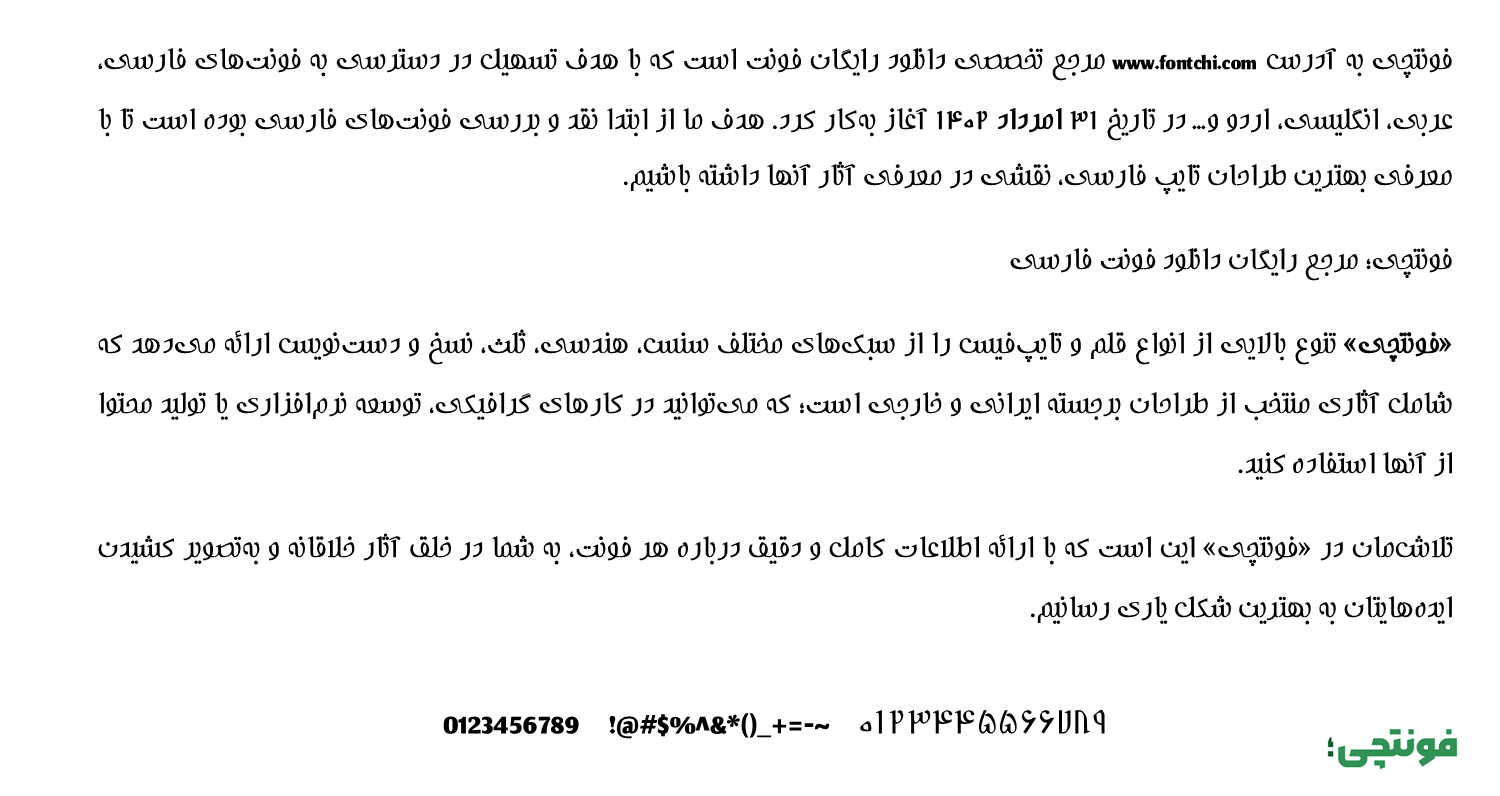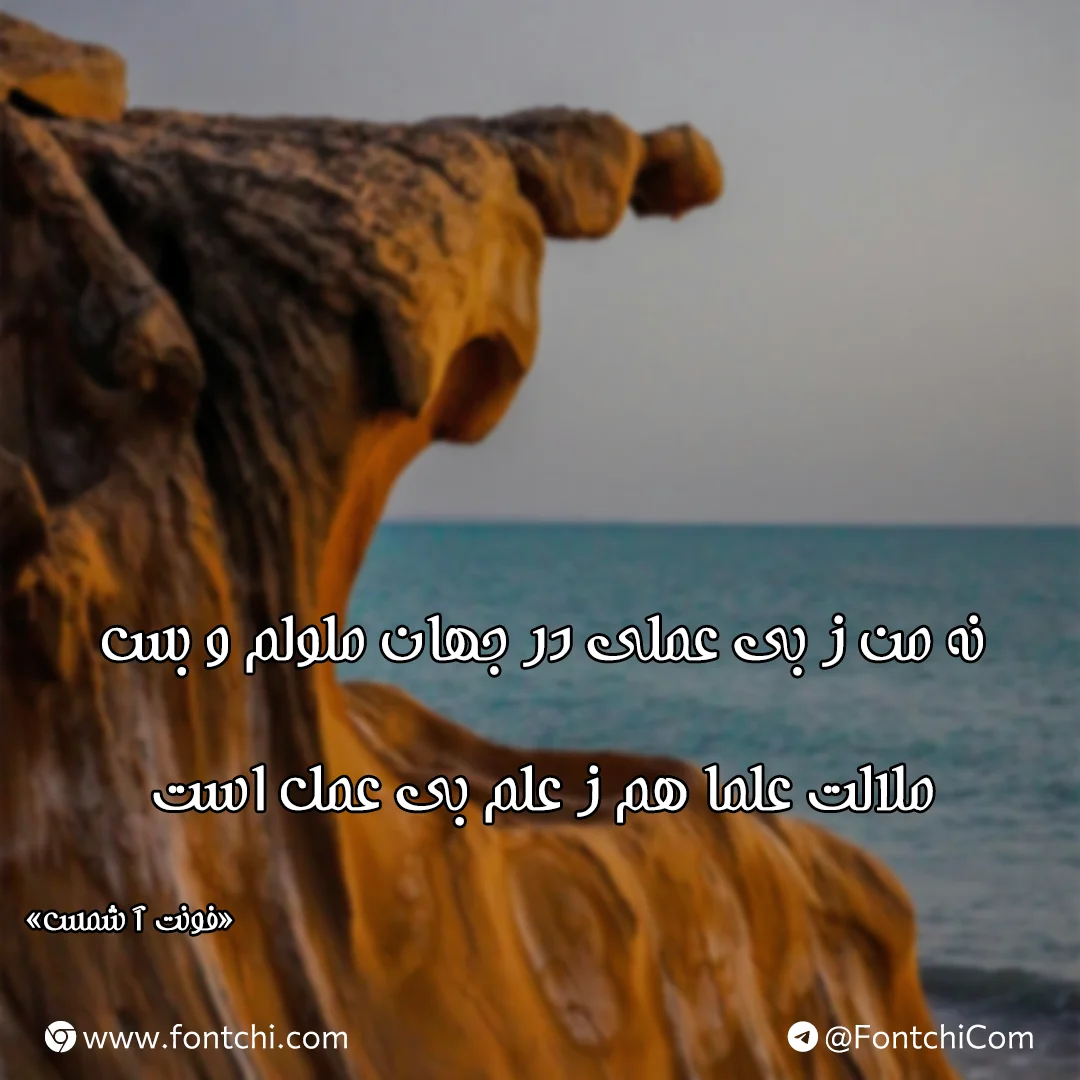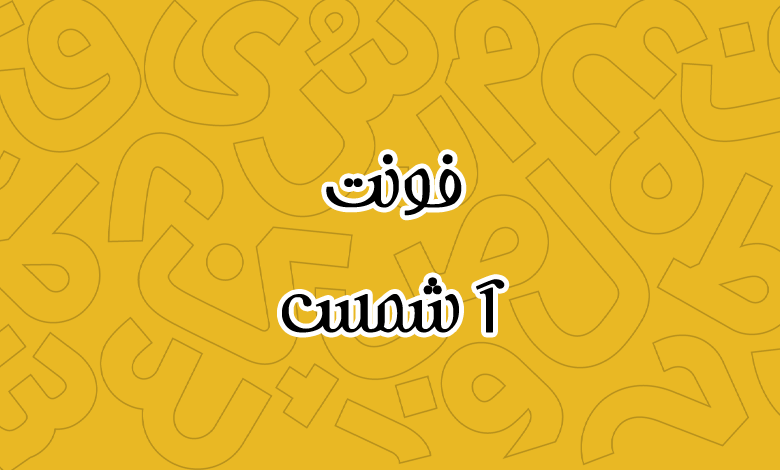
فونت شمس (A Shams)
| نام | آ شمس |
| نام نمایشی | A Shams |
| طراح | محمدرضا شمس الکتابی |
فونت آ شمس یا فونت شمس (A Shams) از سری فونتهای رایگان فارسی است که توسط محمدرضا شمس الکتابی طراحی شده است. این فونت که ظاهری نامنظم، زیبا و در عینحال غیرمنتظره دارد از یک فونت لاتین الهام گرفته شده است.
فونت شمس TTF بوده و با حجمی ناچیز عرضه شده است. این فونت از یک وزن معمولی Regular پشتیبانی میکند که میتوانید از آن در متون کوتاه تا نسبتا بلند استفاده کنید. اما باید درنظر داشت که این فونت برای متنهای بسیار طولانی مانند کتاب مناسب نیست و بیشتر برای کارهای فانتزی توصیه میشود.
این فونت را میتوان گفت که به گونهای در طراحیش از نستعلیق نیز الهام گرفته شده است. به عنوان مثال حروفی همچون «س، ش» دارای ساختاری جوان و بازیگوش هستند که دندانهها در آن حس حرکت و پویایی را منتقل میکنند. در حالی که حروف «الف» در بخش ابتدایی و انتهایی خود دارای ساختاری کشیده در امتدادی نامشخص هستند.
این فونت سنسریف برای استفاده در متوان کوتاه همچون عناوین، تیترها، لوگوها و پوسترهای تبلیغاتی مناسب است که ساختاری فانتزی داشته و با هدف ساختاری نمایشی نوشته میشوند؛ درست جایی که نیاز به دانلود فونت برای جلب توجه هستید. تفاوتی ندارد یک صفحه وب حاوی اسلایدر باشد یا عناوینی که قرار است نگاه کاربران را دزدیده و نرخ کلیک را افزایش دهند.
این فونت در اندازههای بزرگ حس لوکس بودن و مدرنیته را منتقل میکند. در حالی که برای متون بلند، بهویژه با اندازههای پایین چشم را خسته میکند.
فونت شمس فارسی است و از دیگر زبانهای با خطرسم مشترک همچون عربی نیز پشتیبانی میکند. میتوانید کلیه اعراب و کاراکترهای تزئینی که در بالا یا پایین حروف قرار میگیرند را با خیالی آسوده تایپ کنید؛ آنها در همنشینی استانداردی با هم قرار میگیرند.
تنها کاستی این فونت در بخش زبان عدم وجود گلیفهای استاندارد اعداد عربی «٤٥٦» است. از طرفی دیگر زبان انگلیسی در این فونت فاقد گلیف اختصاصی بوده و باید از یک فونت جایگزین و مشابه برای متون دو زبانه فارسی و لاتین استفاده کنید.
کاربردهای این فونت خلاقانه متنوع هستند؛ بیشترین آنها عبارتند از:
- طراحی پوستر برای موضوعات شعر و فرهنگی.
- استفاده در اپلیکیشنهای موبایل که با هدف ایجاد ارتباط بین سنت و مدرنیته هستند.
- استفاده در عنوان کتاب و مجلات بهویژه در موضوعات فانتزی، تاریخی و فرهنگی که ذهن خواننده را جلب کند.
- استفاده در طراحی پست شبکههای اجتماعی چه برای تصاویر عکس نوشته و چه تصاویری که به عنوان تامنیل هستند.